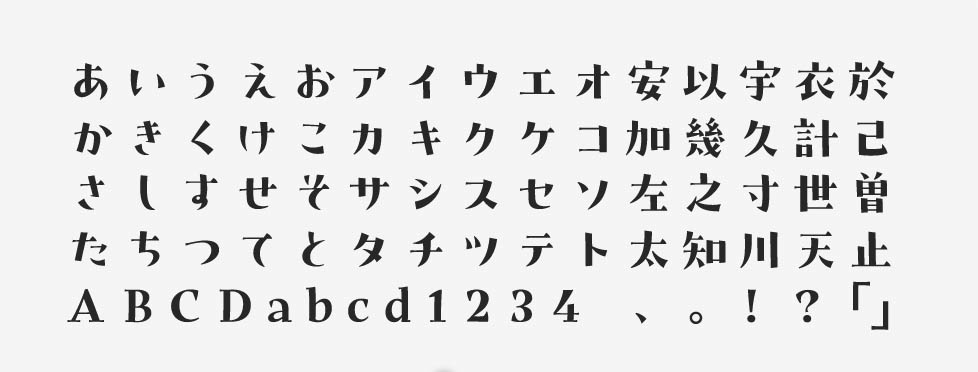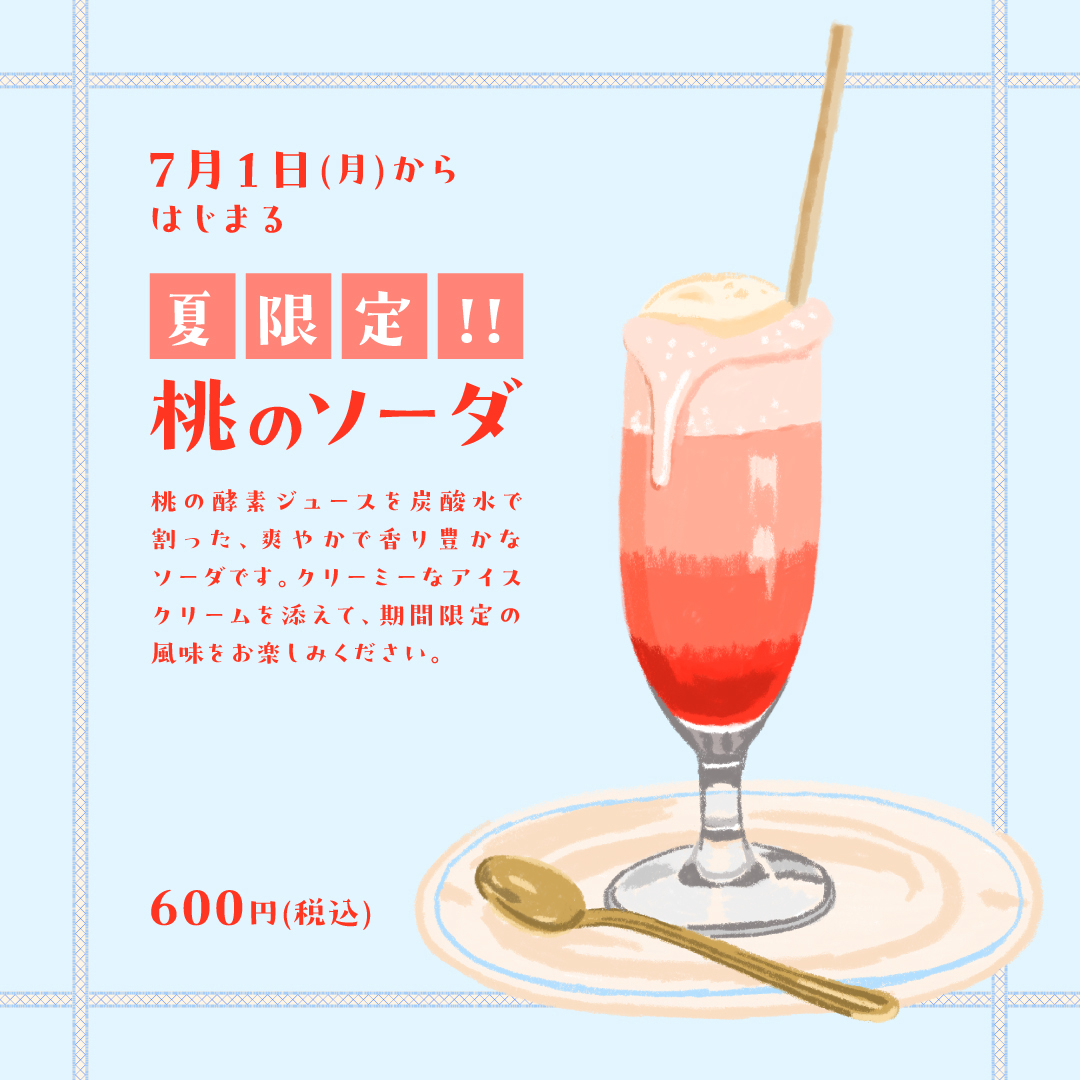
「プフ ソワレ」について
2023年にリリースされたプフ ソワレは、デザイン書体「プフシリーズ」の追加ラインナップとして仲間入りしました。あえて統一しすぎない自由な字形や小さめの字面を特徴としています。それまでの同シリーズがゴシック系の書体が中心であったのに対し、プフ ソワレは明朝体風のデザインです。
「プフ ソワレ」の特徴
プフ ソワレは、商品パッケージや書籍の装丁や動画のテロップなど、幅広い場面で活躍します。可愛らしい印象の文字でありながら、同時にキラキラと輝くエレガントさも兼ね備えていることが魅力と言えるでしょう。
デザインのポイントは、うろこの緩いカーブや、有機的で自然なたわみなどです。右ハライのように徐々に太くなる線は終筆がアーチ状になっていて、そこにも可愛らしさが感じられます。少女漫画などの媒体にもぴったりの雰囲気です。
作例の「レトロ喫茶」のような雰囲気にマッチするプフ ソワレには、手描き感もありますね。可愛い印象がかなり強いフォントですが、文字によっては若干のエレガントさも感じます。日常的なおしゃれなシーンで使える見出し系に強いフォントです。